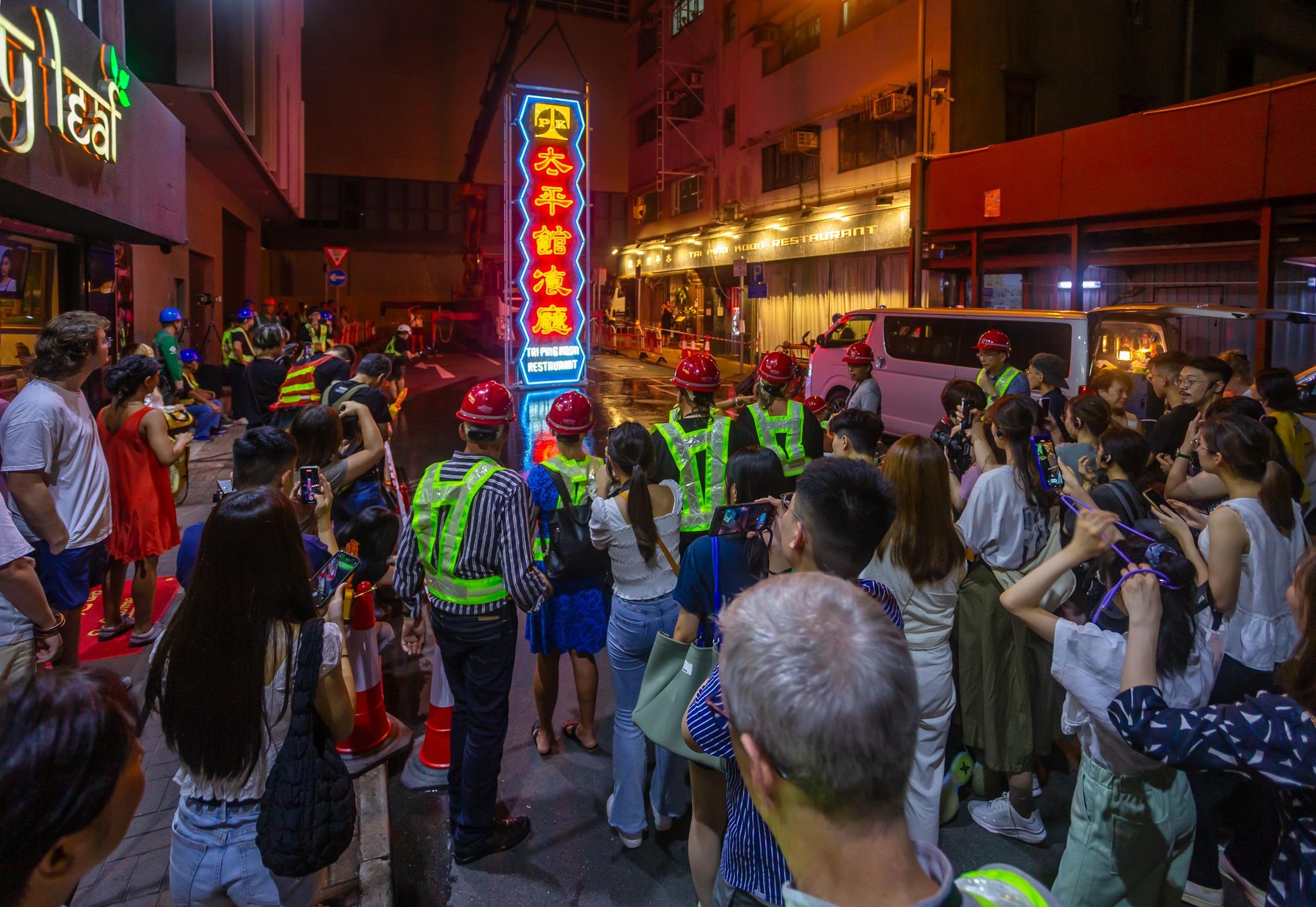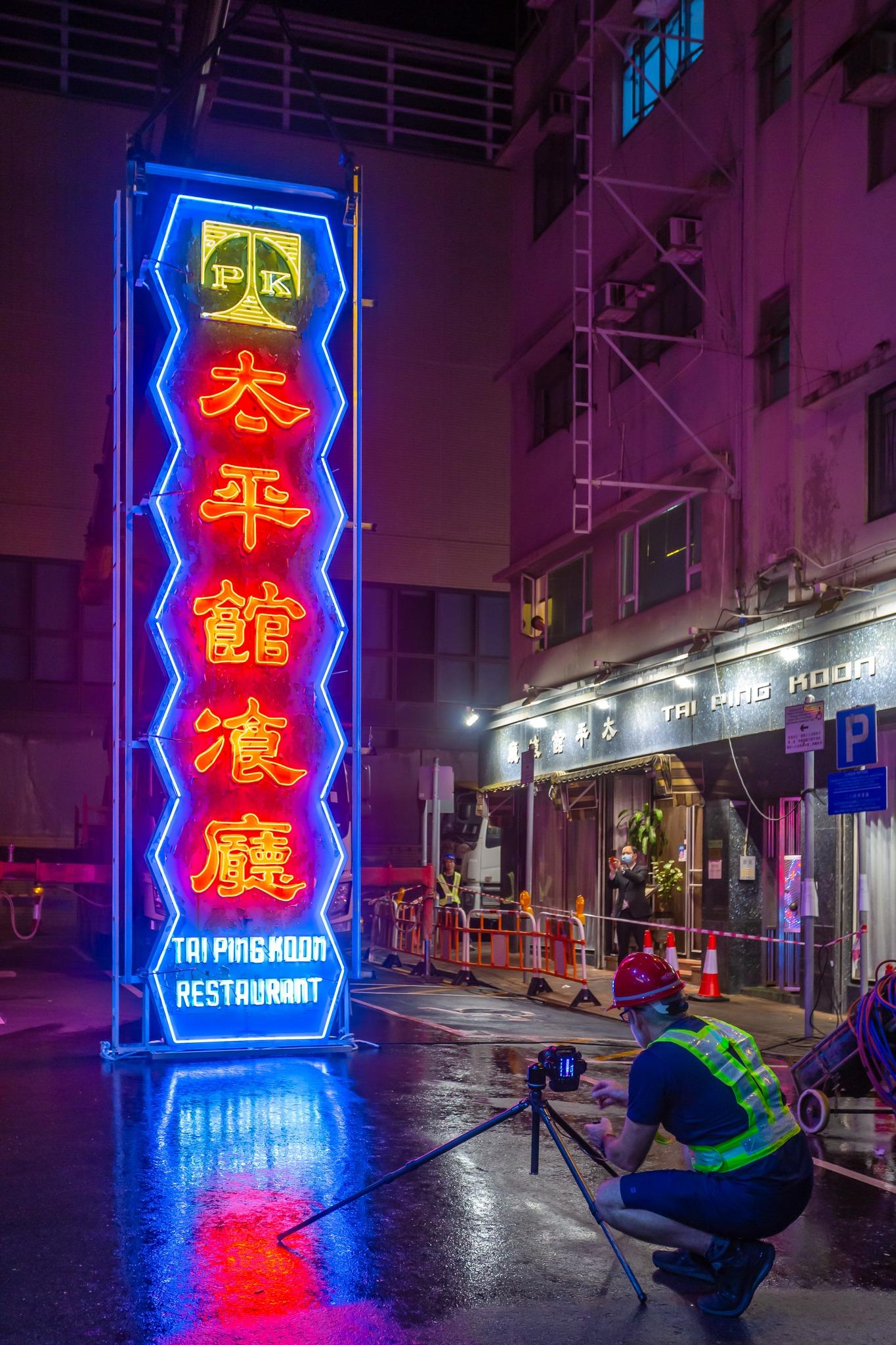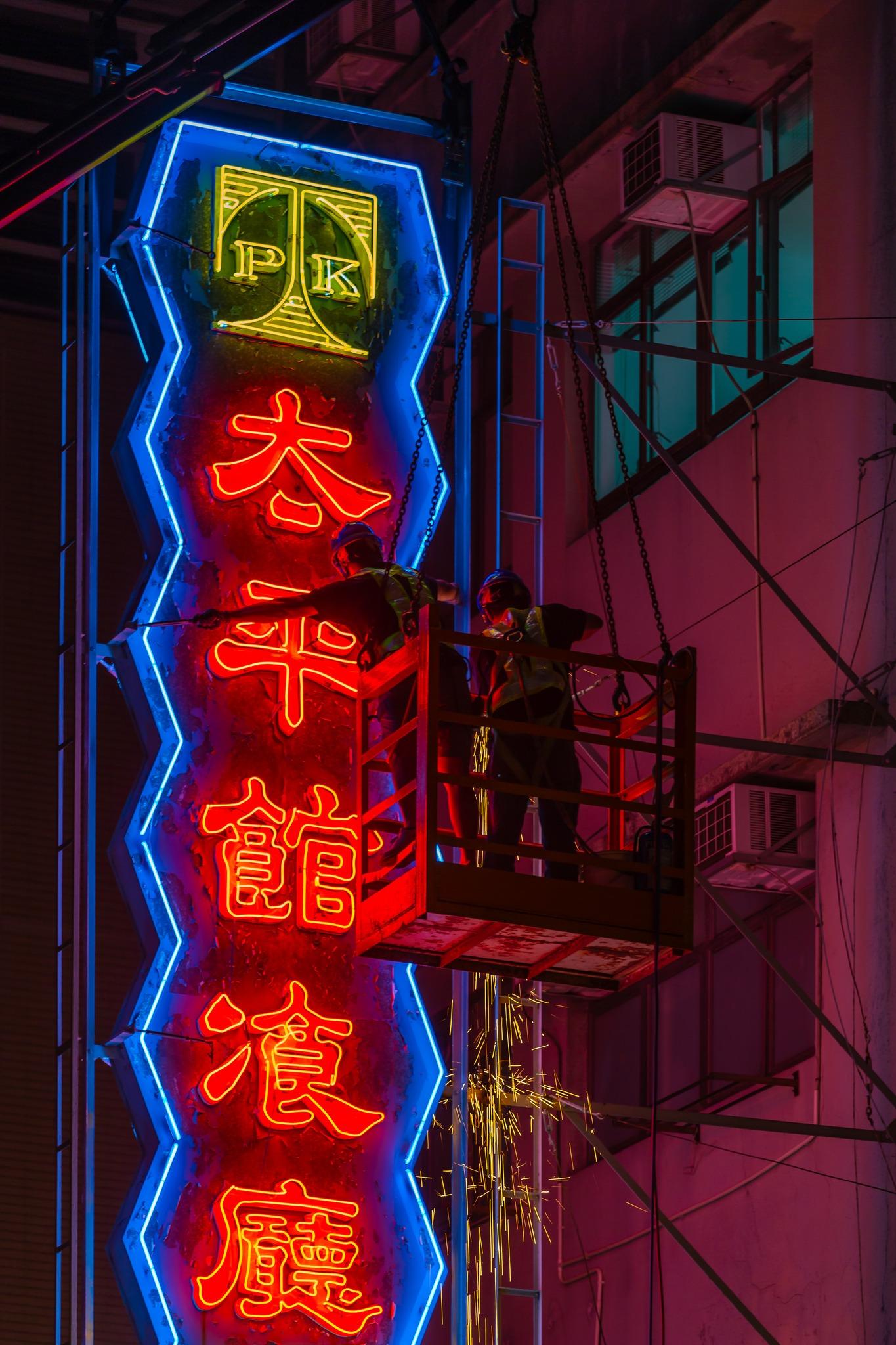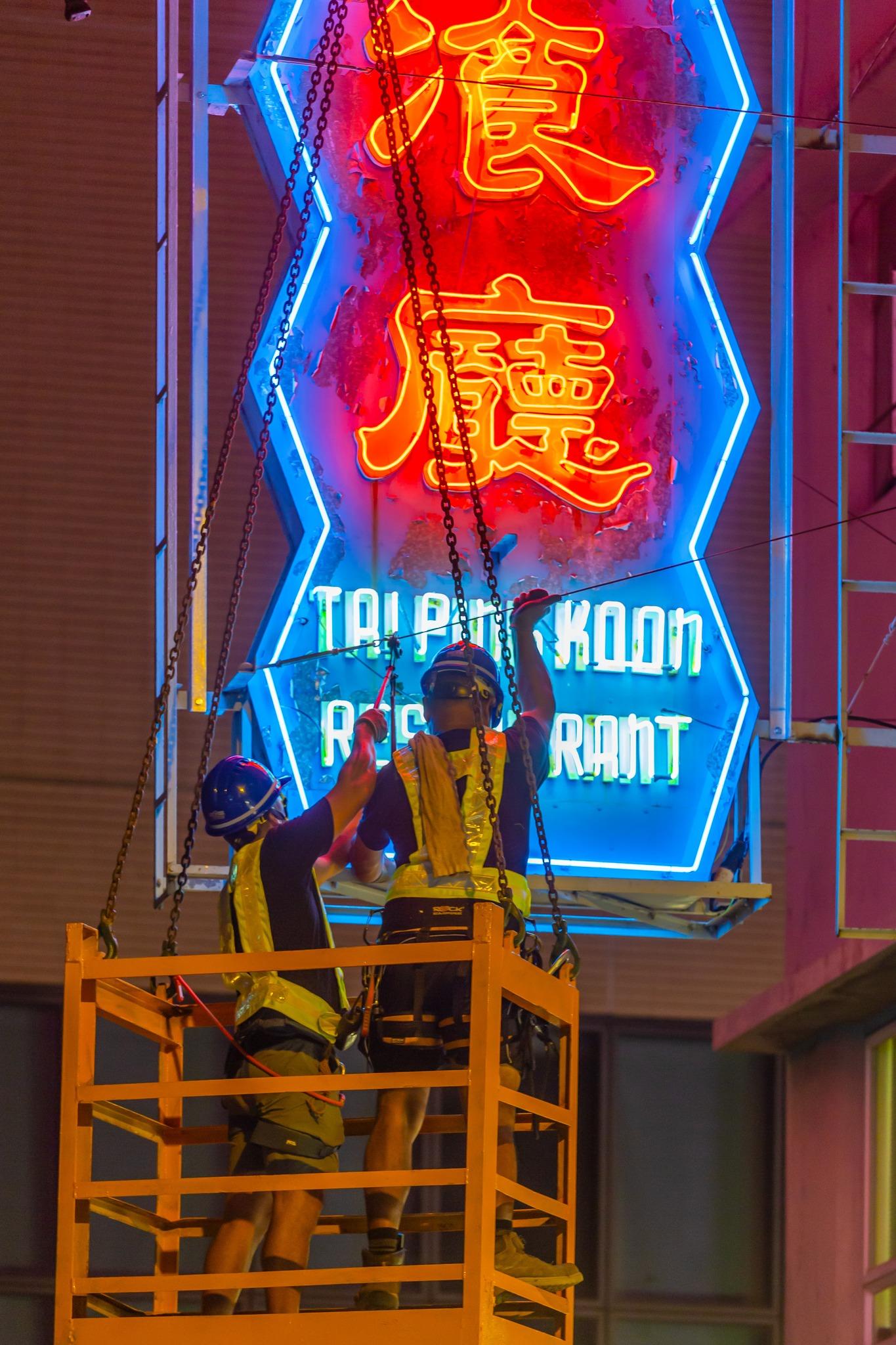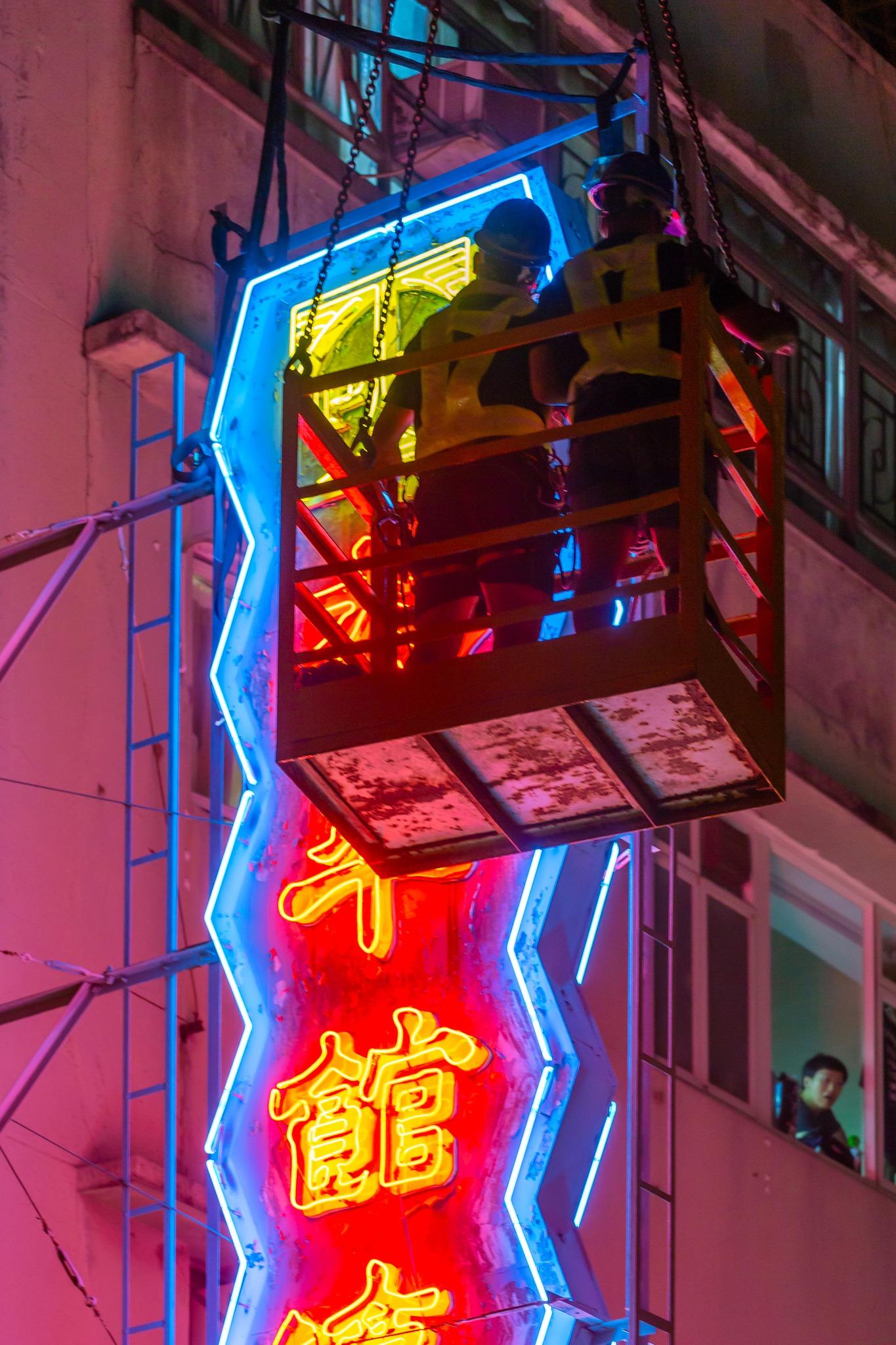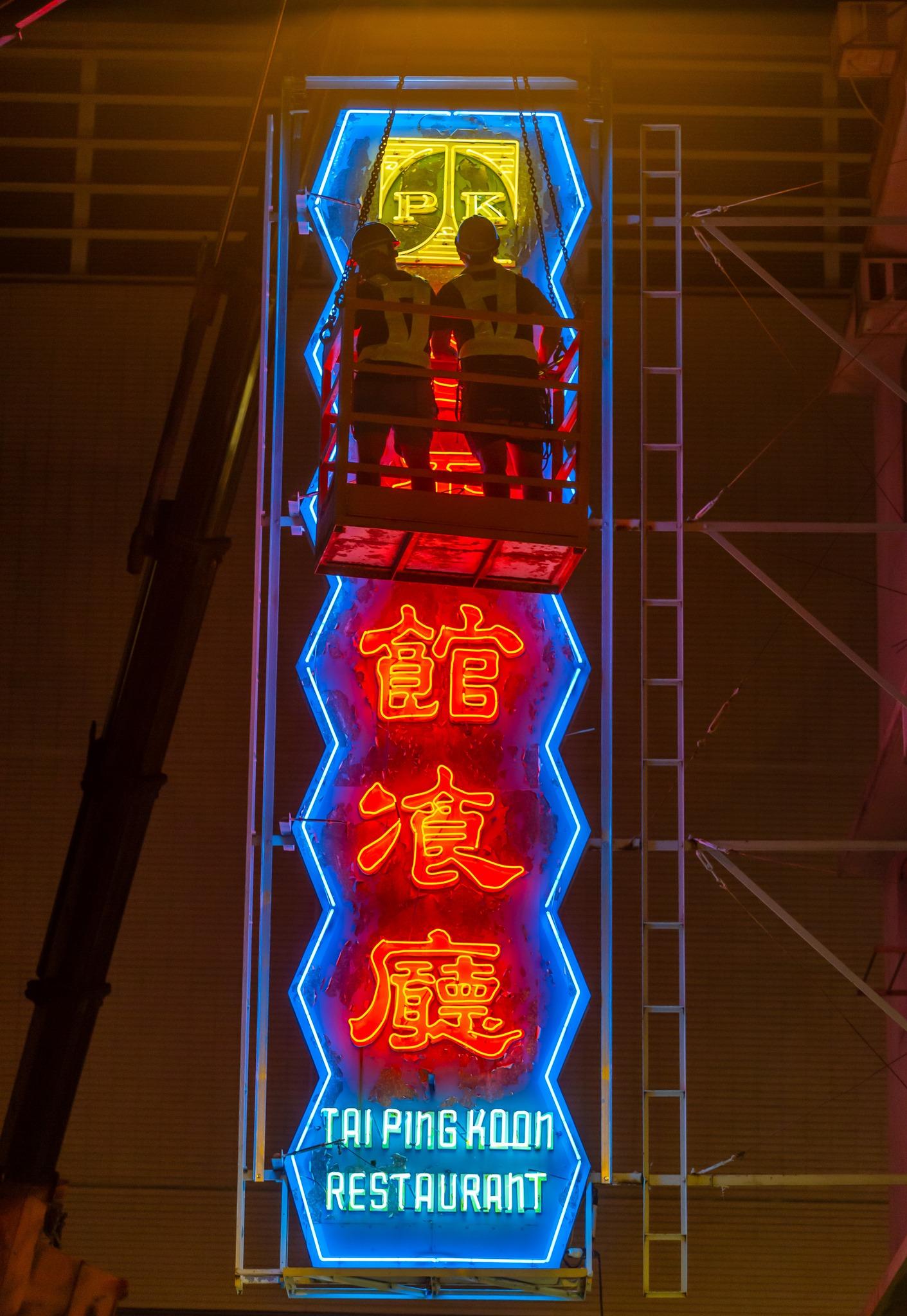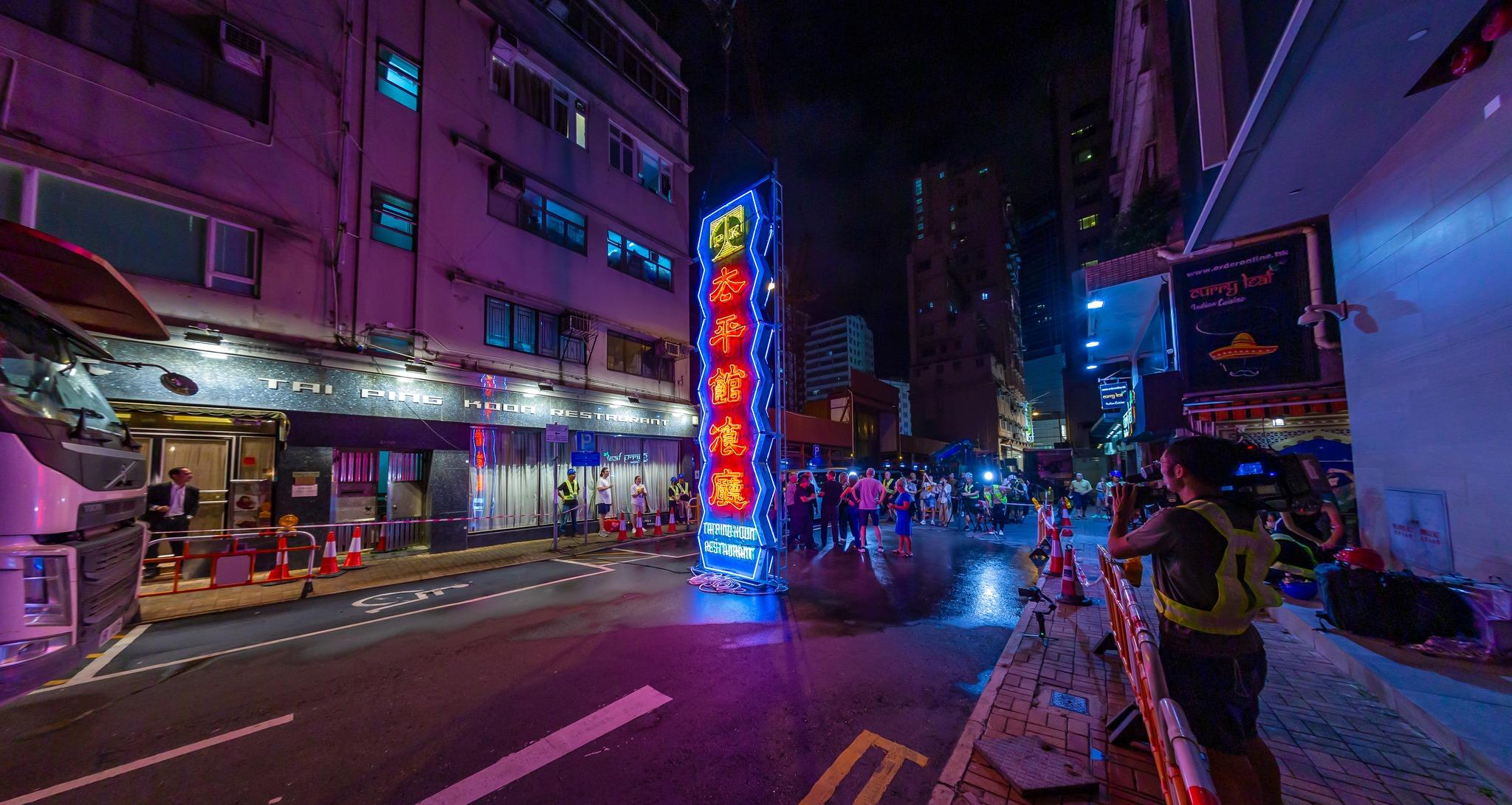
太平館|近60年歷史「太平館餐廳」霓虹招牌落幕 特色字體「飡」堪稱罕見(多圖)
有近60年歷史的「太平館餐廳」霓虹招牌昨日被拆除。(香港老美 老香港的美學印記@fb圖)
創出「豉油西餐的百年老店「太平館餐廳繼尖沙咀老店的霓虹燈招牌於今年2月熄燈拆卸,其擁有近60年歷史的佐敦分店霓虹招牌,昨晚亦熄燈落幕。據了解,招牌會交由機構保存,稍後有機會移師至中環大館重新展出。
有近60年歷史的「太平館餐廳」霓虹招牌昨日被拆除。(香港老美 老香港的美學印記@fb圖) 有近60年歷史的「太平館餐廳」霓虹招牌昨日被拆除。(香港老美 老香港的美學印記@fb圖)
翻查資料,「太平館餐廳佐敦分店的霓虹招牌,在1964年開業時已經掛上,默默見證佐敦變遷近60年。據指招牌的特色之處是字體出自「嶺南才子」陳荊鴻的手筆,其中太平館餐廳的「餐」字寫成「飡」,在香港招牌史上甚為罕見,惟招牌不獲政府批准保留,直到昨晚終於拆卸。人稱臣哥的資深傳媒工作者,在其社交網站紀錄今次拆除招牌事件。